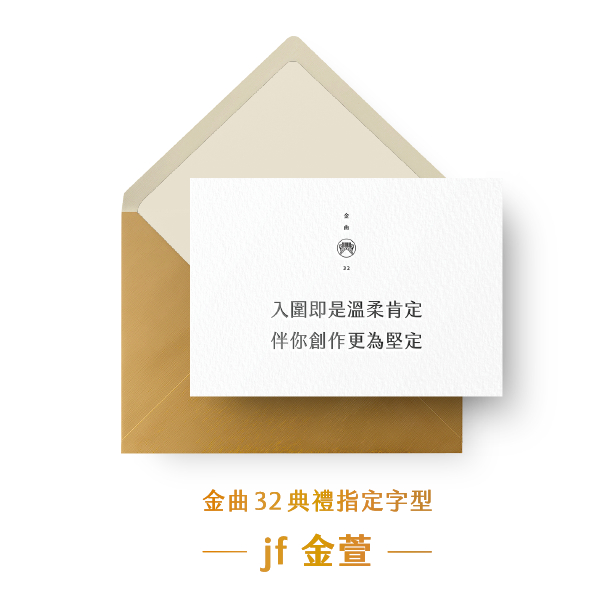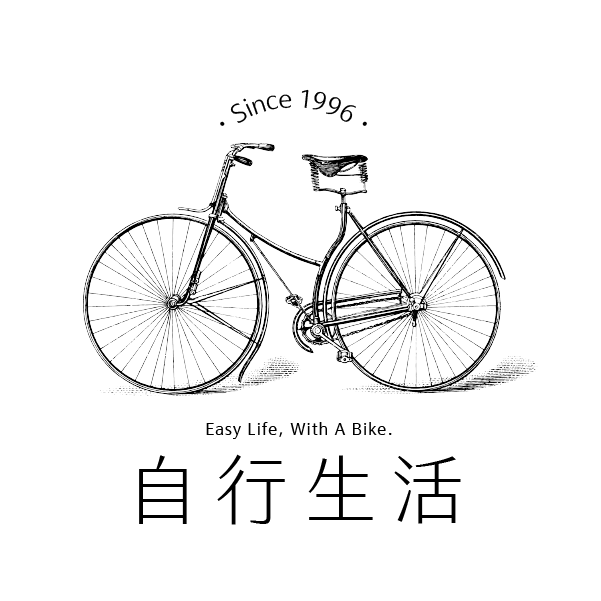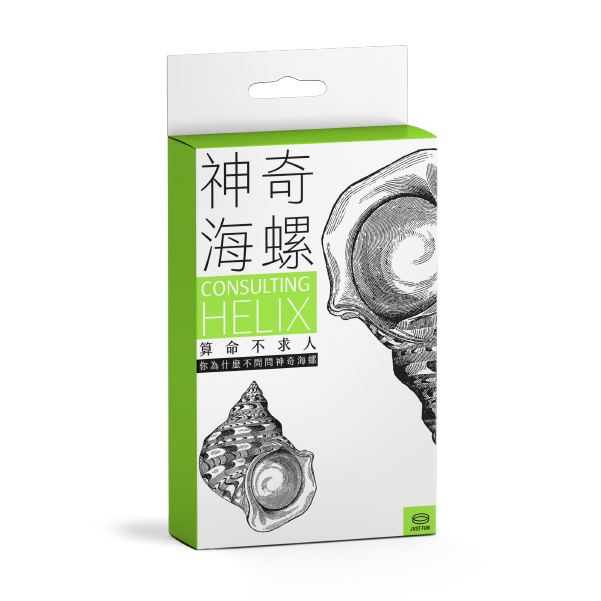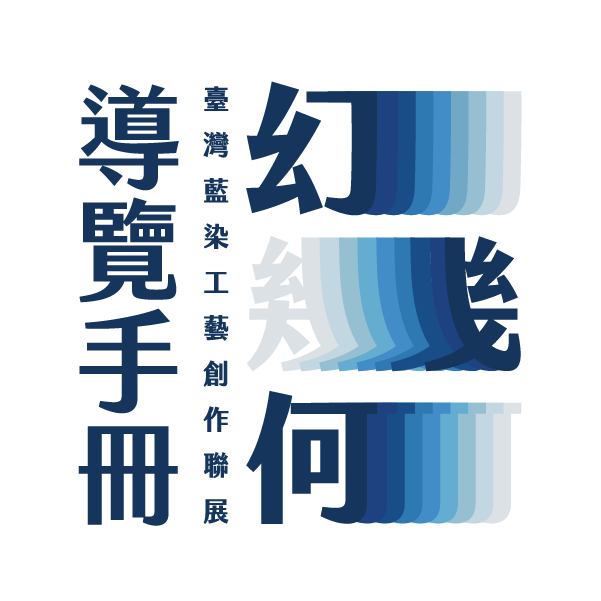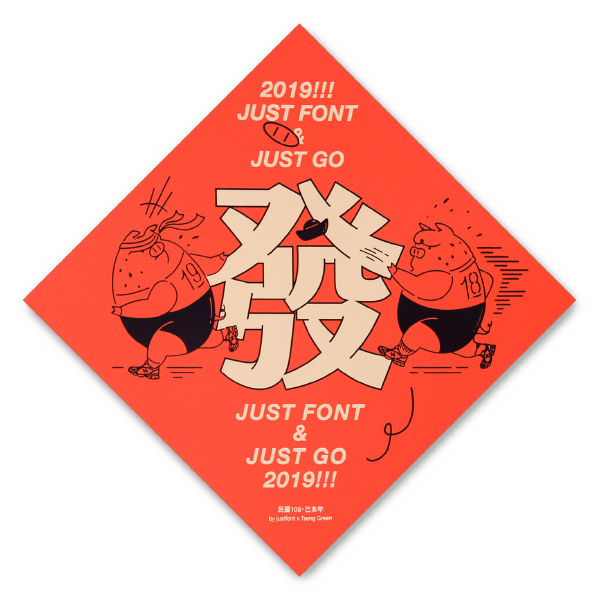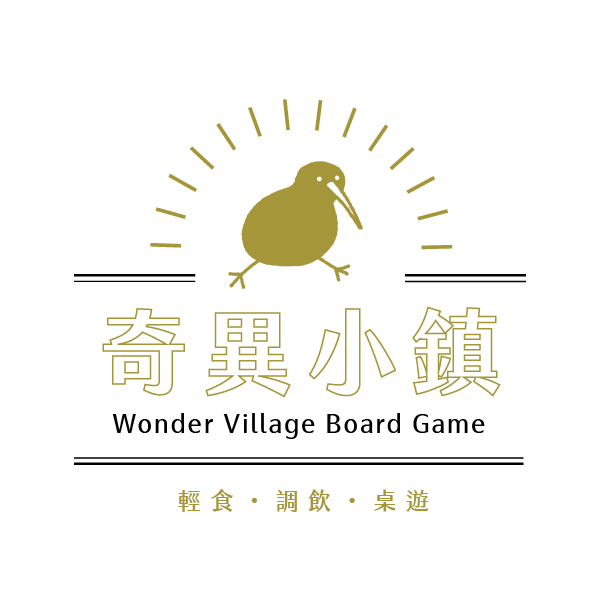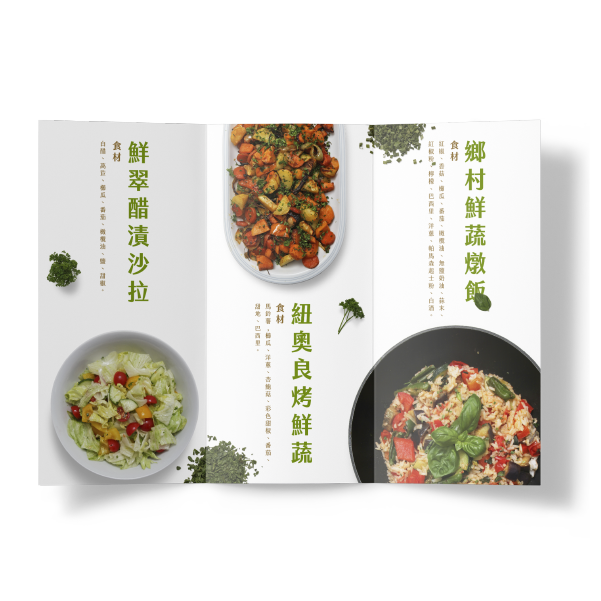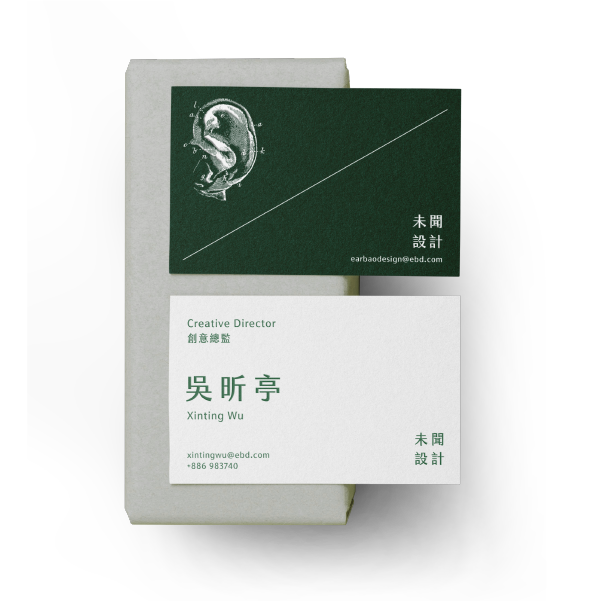
jf 金萱
9 種字重
金萱是明黑混合的風格,
呈現出清爽明快的感受,
應用範圍廣泛,
是基本字型以外的最佳選擇。
字型設計師
林霞
宜蘭人,justfont 字體總監,30 年字體設計經驗。催生金萱、金萱那提與蘭陽等字型系列,並在凝書體、激燃體與臺灣道路體創作過程中擔任總顧問。喜歡開車。每天一號表情盯著螢幕,幻想著今天到印度,下一站到歐洲,然後再計劃到南美洲,環遊世界。